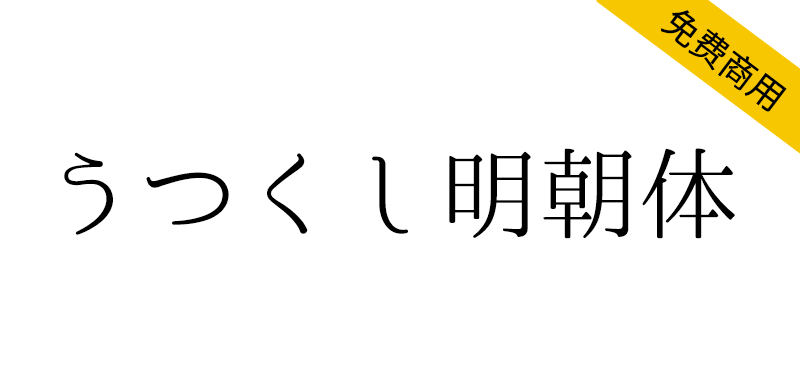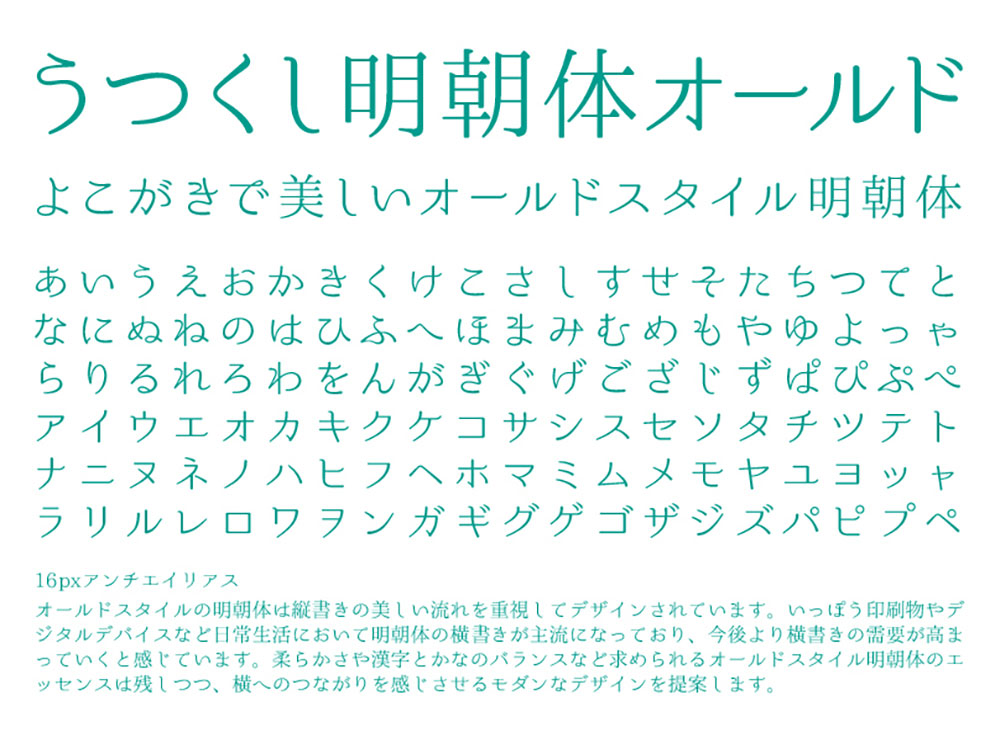
うつくし明朝体基本上是重视竖写的美丽流程而设计的。在印刷品和数码设备等日常生活中,明朝体的横写成为主流,今后横写的需求会更加高涨。“うつくし明朝体+” 在保留古典明朝体的要素,如柔和、复古的风味以及汉字和假名的平衡等的基础上,采用了更现代的设计,强调与横排的连接感。垂直和水平的线条都是笔直的,同时也广泛使用了斜线的直线设计。这是对新概念的古典系列明朝体的设计提案。平假名和片假名赢得了2014年日本印刷年鉴最佳作品奖。
オールドスタイル明朝体は、基本的に縦書きの美しい流れを重視してデザインされています。印刷物やデジタルデバイスなど日常生活において明朝体の横書きが主流になっており、今後はより横書きの需要が高まっていくと感じています。うつくし明朝体+は柔らかさ・レトロな味わい・漢字とかなのバランスなど求められるオールドスタイル明朝体のエッセンスは残しつつ、横へのつながりを感じさせるモダンなデザインにしました。垂直水平のラインはまっすぐに、また斜めのラインもまっすぐなデザイン多用しました。新しいコンセプトのオールド系明朝体のデザイン提案です。ひらがな・カタカナは日本タイポグラフィ年鑑2014ベストワーク賞。